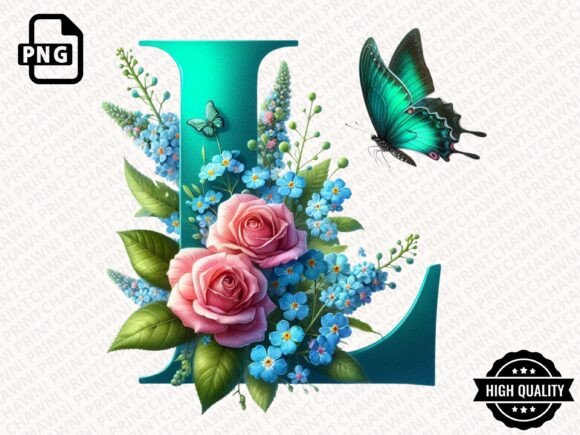
Roses & Butterflies Alphabet Clipart PNG
قد يكون العثور على عناصر التصميم المناسبة أمرًا صعبًا، ولكن Roses & Butterflies Alphabet Clipart PNG يقدم مجموعة استثنائية ترتقي بعملك على الفور.